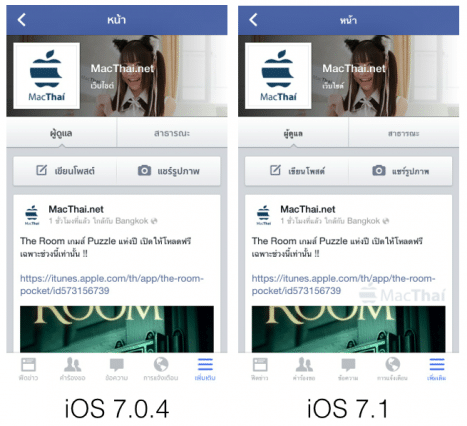
ระบบภาษาไทยใหม่ใน iOS 7.1 ยกเลิกใช้ฟอนต์ภาษาไทยแบบไม่มีหัวแล้ว
หลังจากที่แอปเปิลออก iOS 7.1 อย่างเป็นทางการแล้ว ก็พบว่ามีการเปลี่ยนแปลงเรื่องฟอนต์ภาษาไทยตามข่าวที่เคยเห็นในเวอร์ชัน Beta โดยในครั้งนี้เป็นการเปลี่ยนฟอนต์ภาษาไทยจากที่ไม่มีหัว มาเป็นแบบที่มีหัว เช่นเดียวกับ iOS 6 ก่อนหน้านี้อีกครั้ง
โดยก่อนหน้านี้แอปเปิลได้เคยใช้ฟอนต์ธนบุรีที่มีหัวมาตลอด จนเมื่อมีการเปิดตัว iOS 7 ได้มีการตัดสินใจเปลี่ยนฟอนต์ภาษาไทยไปเป็นฟอนต์สุขุมวิทซึ่งไม่มีหัว ซึ่งเกิดเสียงวิจารณ์อย่างหนักว่าอ่านยากกว่าเดิม
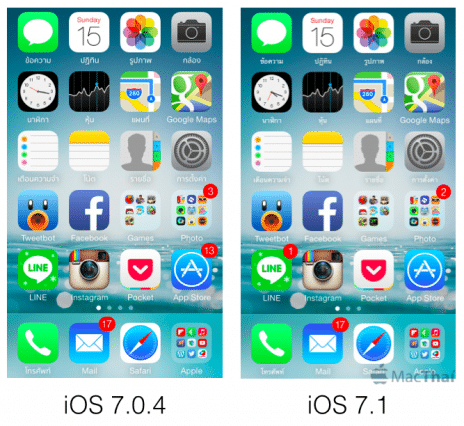
ล่าสุดแอปเปิลได้เปลี่ยนฟอนต์ภาษาไทยบน iOS 7.1 ให้กลับมาเป็นฟอนต์ธนบุรีเช่นเดิมแล้ว จากการตรวจสอบพบว่าไม่มีจุดไหนที่มีฟอนต์ภาษาไทยแบบไม่มีหัวอยู่เลย
โดยส่วนตัวคิดว่านี่เป็นการเปลี่ยนที่ถูกต้องครับ ถึงแม้หลายคนจะเคยชินกับฟอนต์ภาษาไทยที่ไม่มีหัวบน iOS 7 กันแล้วแต่สำหรับการใช้งานจริง ฟอนต์ธนบุรีซึ่งมีหัวอ่านง่ายกว่าและเคยชินกับชาวไทยมากกว่า